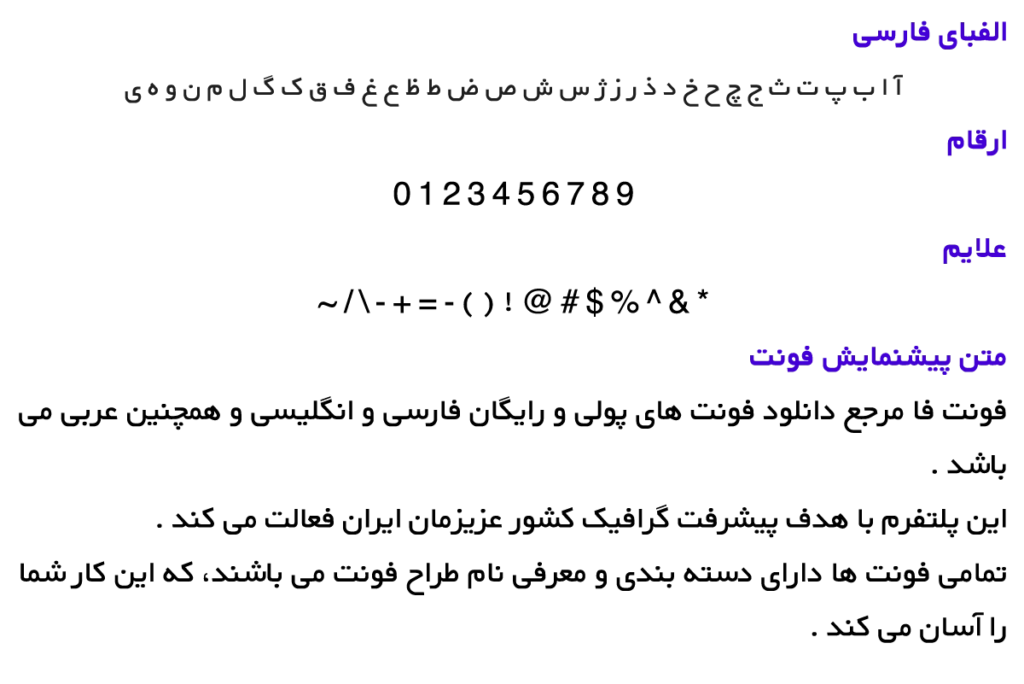
فونت فارسی یکان پلاس – B Yekan Plus
سال ساخت فونت: 1393
طراح فونت: علی سواری نوع فونت: فونت عنوان و فونت متن
توضیحات و معرفی فونت یکان پلاس
فونت فارسی یکان پلاس ( B Yekan Plus ) از مجموعه فونت های برتر و سری B می باشد، همچنان نوع فونت عنوان و متن می باشد.
فونت شگفت انگیز و زیبای فوق توسط علی سواری در سال 1393 طراحی و ساخته شده است.
همچنان فونت در 2 وزن پر رنگ و معمولی است.
در لیست زیر می توانید وزن های این فونت شگفت انگیز و زیبا را ببینید.
- B Yekan Plus Bold
- B Yekan Plus Regular
در عکس زیر می توانید پیشنمایش زیبایی از این تایپ فیس ببینید که باهاش شعر قدیمی ایران نوشته شده است.
در تصویر زیر نیز میتوانید تفاوت کلی این تایپ فیس را با فونت بی یکان مقایسه کنید.